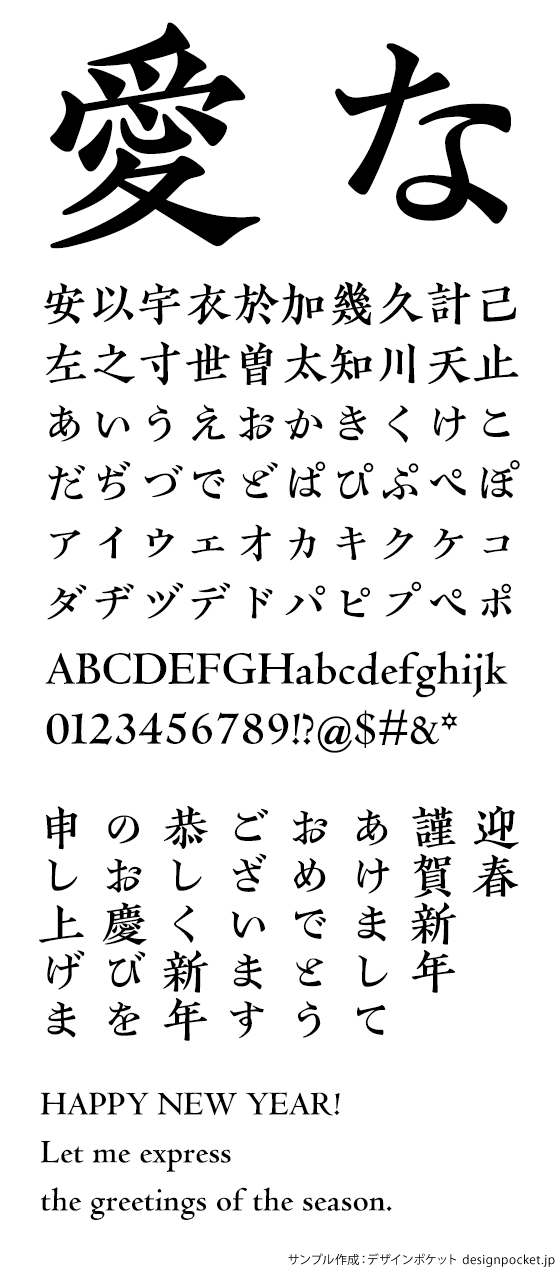
宋朝体
KOにしき陳起B
KONishikiChinki-B
『Book of Specimens』(平野活版製造所、1877)所収の「第三號」ひらがな活字を復刻した「にしき」に、『南宋羣賢小集』(陳宅書籍鋪、1208—1264)に用いられた字様をもとに翻刻した臨安宋朝体「陳起」、ニコラ・ジェンソンの活字を使用したプリニウス著『博物誌』(1472)から復刻したヴェネチアン・ローマン体「K.E.Aries」を組み合わせた「KOにしき陳起M」のファミリーで、ボールド・ウエイトです。
KOにしき陳起B